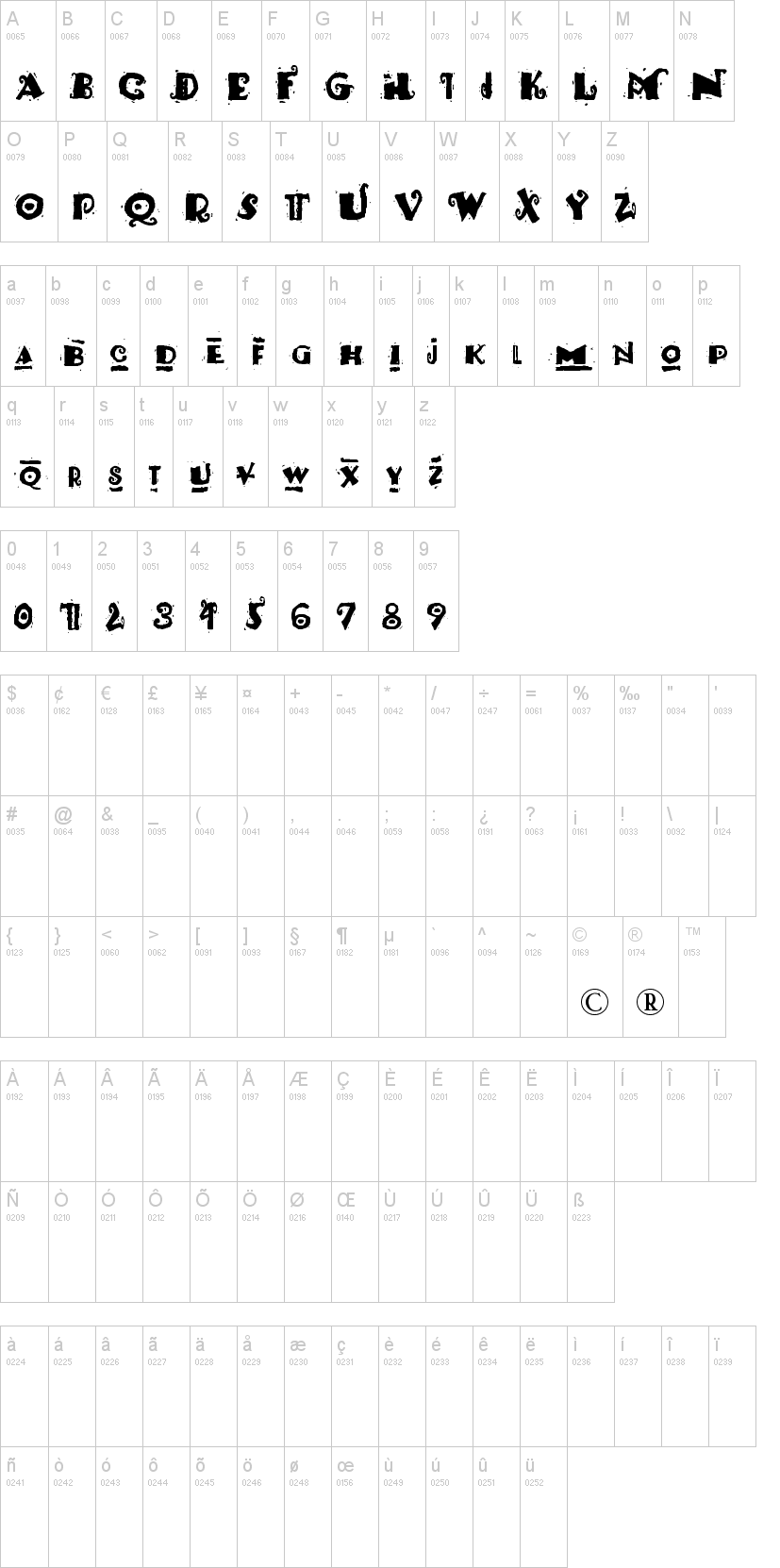
Pauls South Pacific
Pauls South Pacific是一种字体,它的设计灵感来自于南太平洋的传统艺术元素。这种字体的特点是线条流畅、粗犷有力,字母之间的间隔相对较大,因此具有很好的可读性。Pauls South Pacific字体的使用范围广泛,可以用于海报、广告、书籍、标志、包装等多种设计领域。它是一种独特的字体,可以让设计作品更具有个性和民族特色。
Pauls South Pacific是一款非常不错的手写艺术字体,具有很好的视觉感,适合于文化类的宣传设计、商业类品牌的广告和产品包装设计以及个性化文字排版等较多场景。